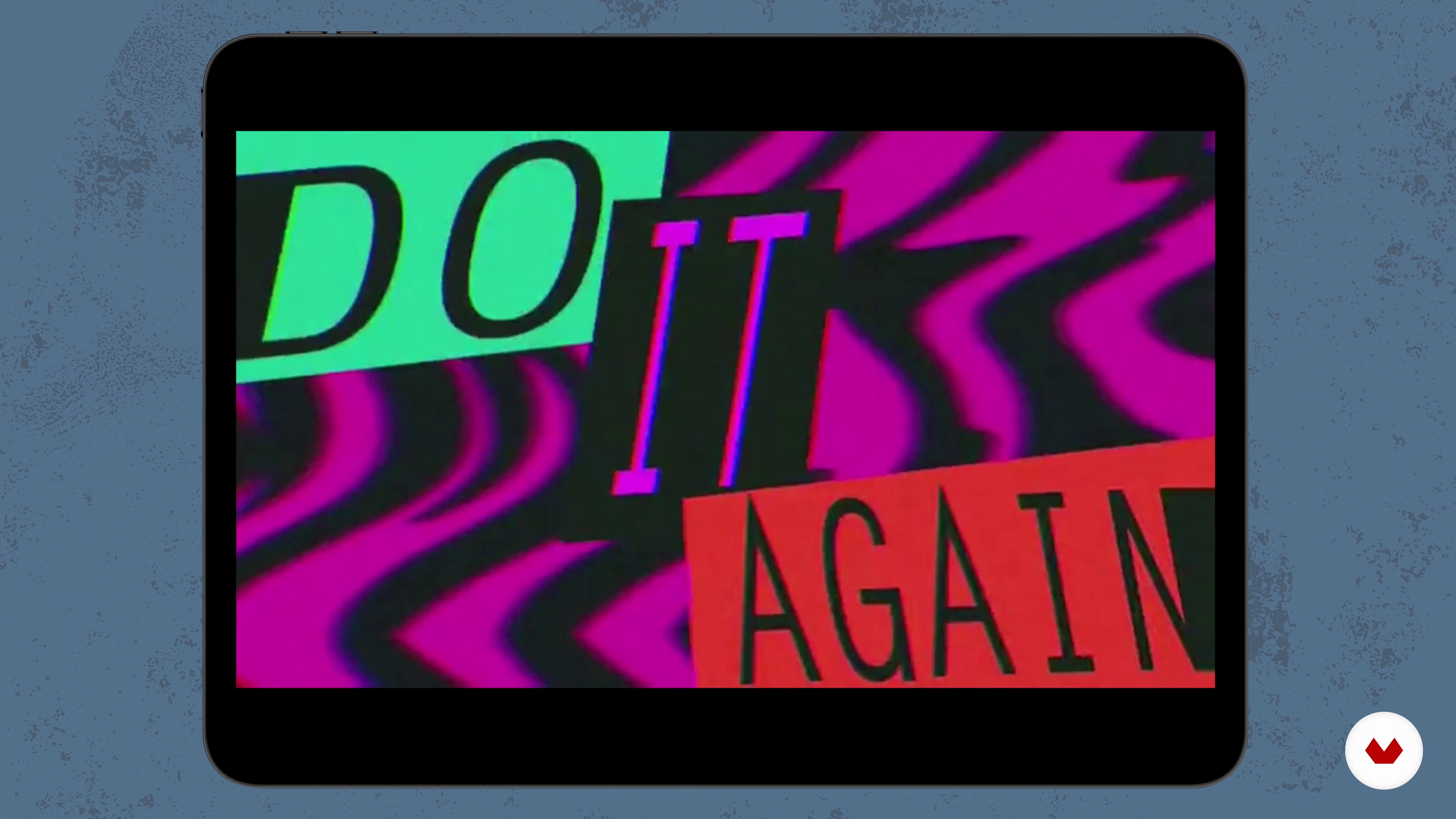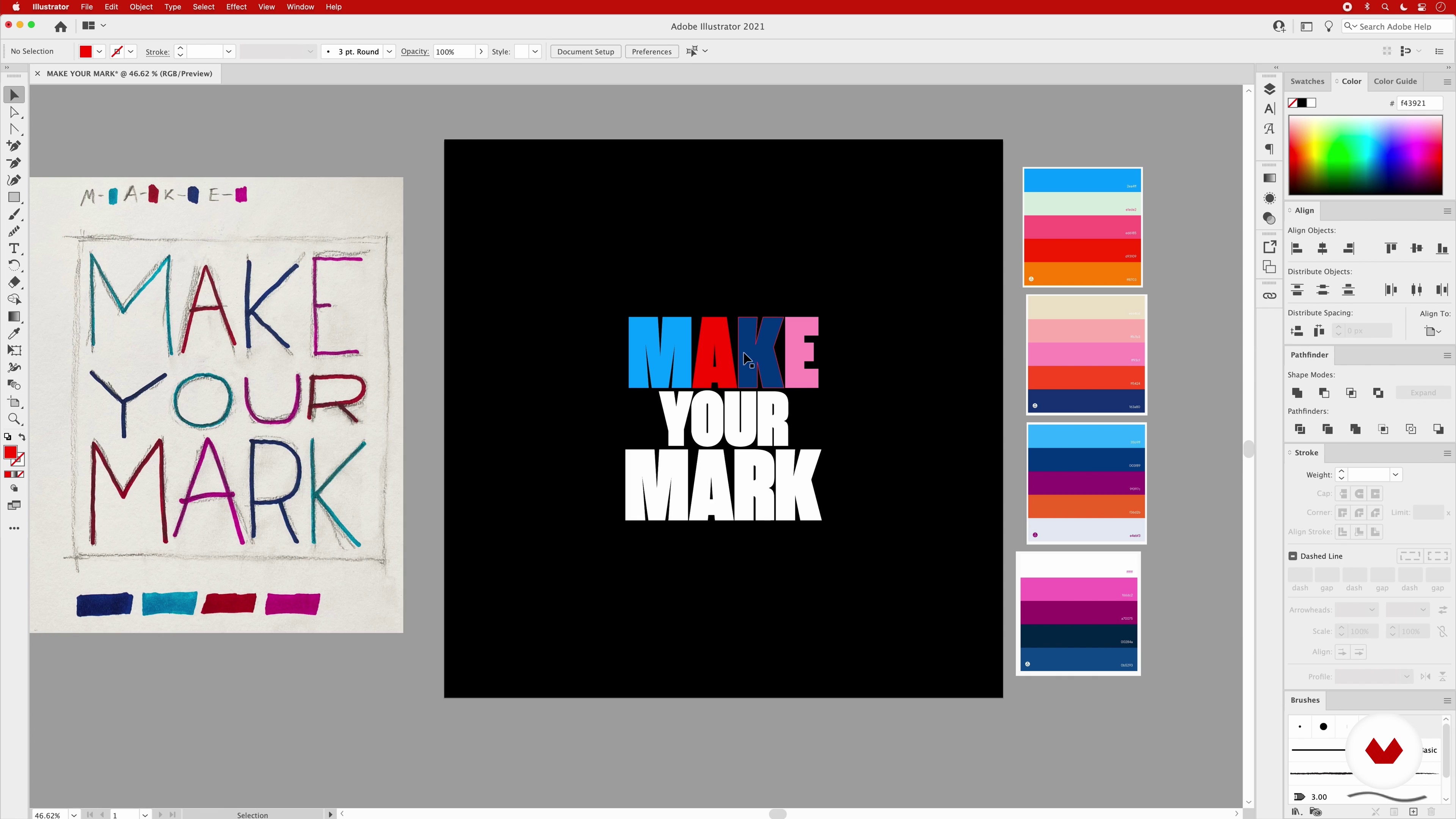
No mundo da tipografia, as letras valem mais do que mil palavras, principalmente quando a animação entra em jogo. O designer gráfico e motion designer Mat Voyce é conhecido por transformar tipografias expressivas em animações dinâmicas e divertidas. Ele já colaborou com grandes marcas como Netflix, Disney+, Adobe e BBC.
Neste curso, você entrará para o mundo da animação e aprenderá a dar vida à sua tipografia. Seu professor ensinará você a expressar uma ideia ou frase criando um design original no Illustrator e agregando movimento no After Effects. No final, você poderá compartilhar com o mundo uma peça de tipografia animada e divertida feita por você.
Você iniciará esta aventura conhecendo o Mat Voyce, seu professor neste curso. Ele contará sobre sua jornada profissional no design gráfico e tipografia. Também falará dos designers que influenciaram seu trabalho e quais são suas fontes de inspiração.
Em seguida, você entrará para o mundo da tipografia cinética descobrindo referências e explorando os fundamentos básicos do Illustrator e do After Effects. Você escolherá a frase que deseja animar e entenderá os tipos de letras disponíveis para selecionar seu favorito. Logo, investigará as cores para criar uma paleta adequada à sua ideia.
Na terceira unidade, você mergulhará de cabeça na fase do design, criando um esboço no papel e digitalizando-o para trabalhar no Illustrator. Você aprenderá a criar uma camada de base com a sua frase e descobrirá como dar um toque contemporâneo à sua peça. Verá como aplicar sua paleta de cores e experimentará com várias combinações. Depois, você importará seu design no After Effects e entenderá como animar a sua frase. Adicionará texturas e efeitos dentro do programa, transmitindo uma sensação artesanal às suas letras.
Para concluir, você exportará sua animação em diversos formatos para as plataformas online. Você também aprenderá a transformar sua animação em um GIF utilizando o Photoshop. Por último, Mat dará dicas para você compartilhar seu trabalho nas redes sociais.
Você fará o design de uma tipografia e animará uma frase com ela.
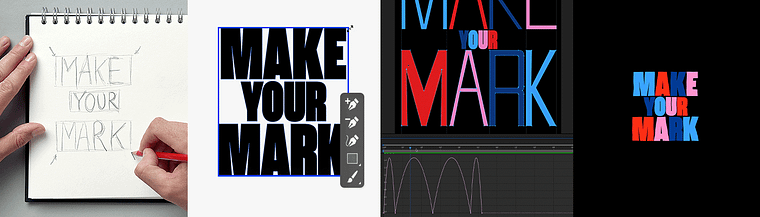
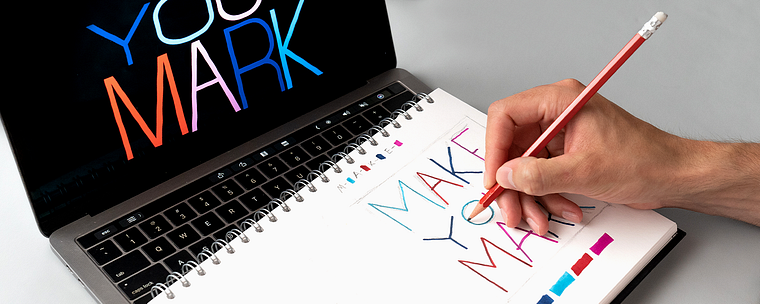
O curso ensina a integrar tipografia animada em diretrizes de marca, criar ativos de motion design e planejar fluxos de trabalho eficientes para projetos com clientes e narrativas visuais.
Os temas incluem fundamentos da tipografia cinética, lettering vetorial no Illustrator, animação de texto no After Effects, pesquisa de frases, seleção de paletas de cores, esboço e exportação de ativos animados.